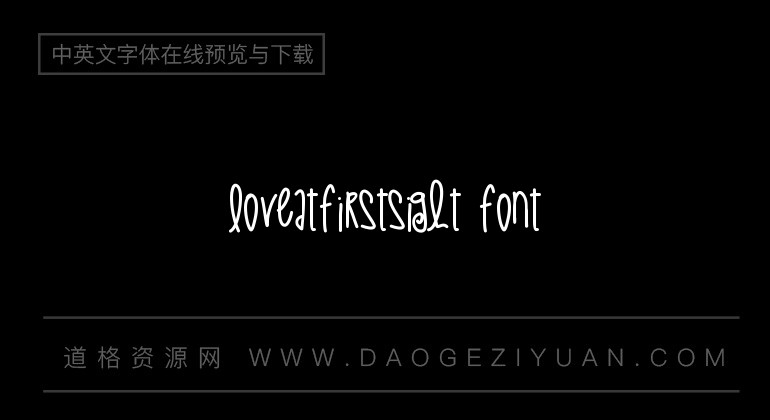
LoveAtFirstSight Font 是一种手写风格的字体,适用于各种设计项目,例如卡片、海报、标志、商标等等。它的特点是有很多连笔,使得字体看起来非常流畅和自然。此外,它的字母也非常漂亮,给人一种温暖和舒适的感觉。 LoveAtFirstSight Font 提供了多种字形和大小,使得用户可以轻松地根据需要调整字体的外观。因此,它是一种非常受欢迎的字体,特别是在浪漫或温馨的设计领域中。内容介绍
LoveAtFirstSight Font是一款非常不错的手写艺术字体,具有很好的视觉感,适合于文化类的宣传设计、商业类品牌的广告和产品包装设计以及个性化文字排版等较多场景。